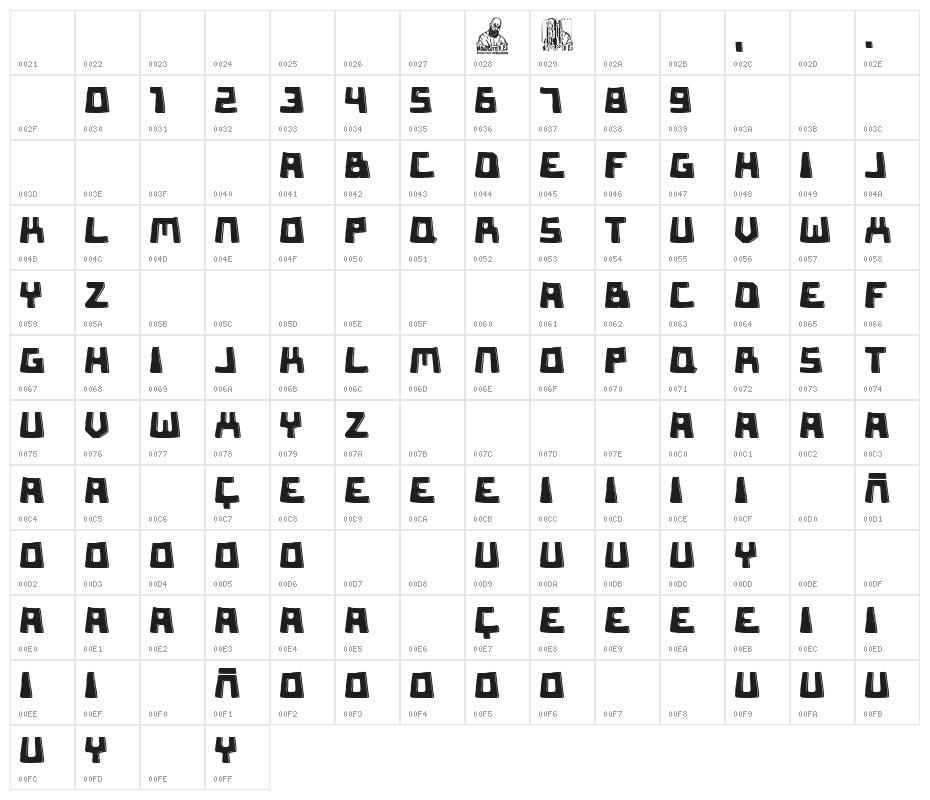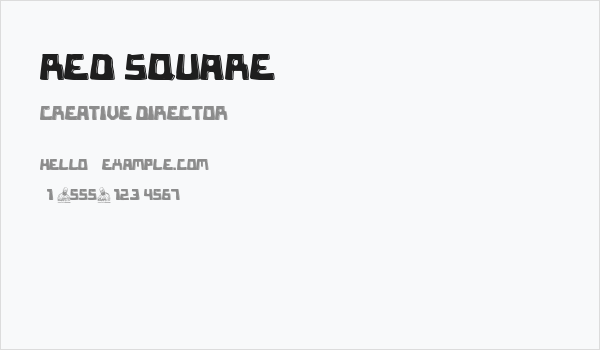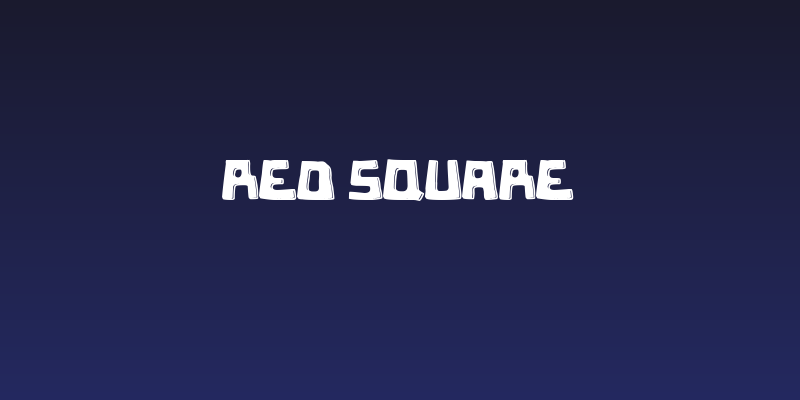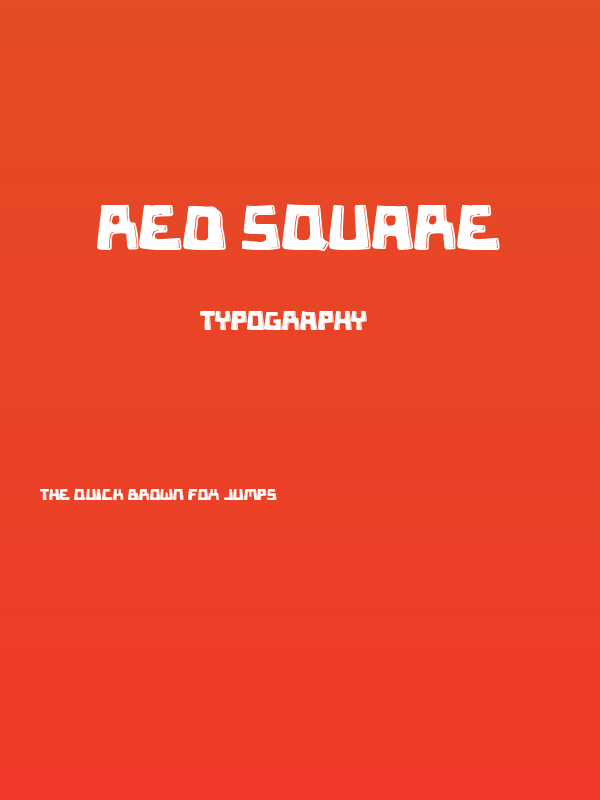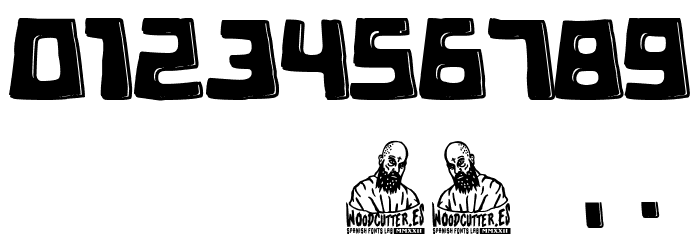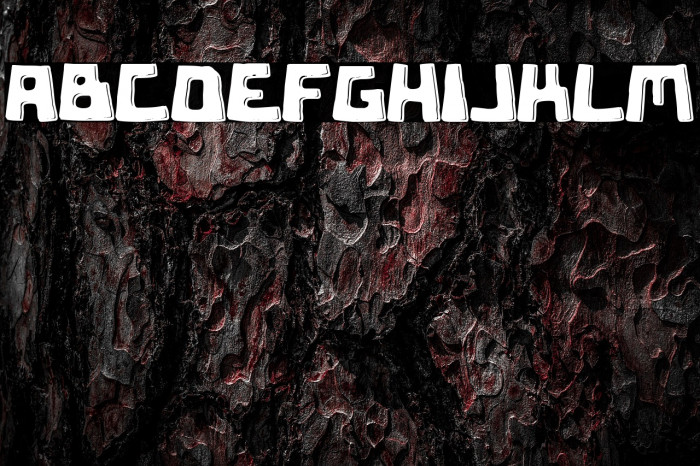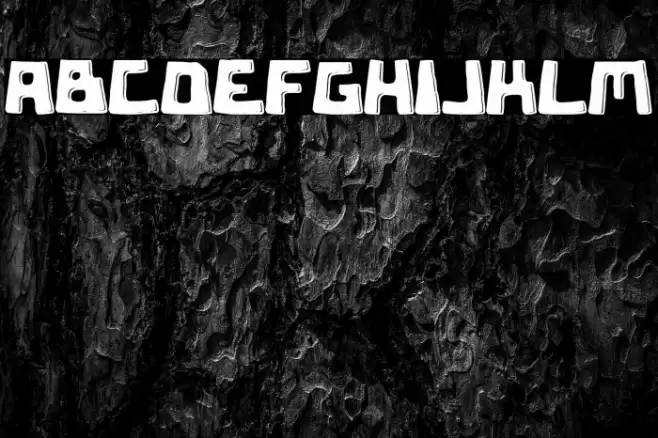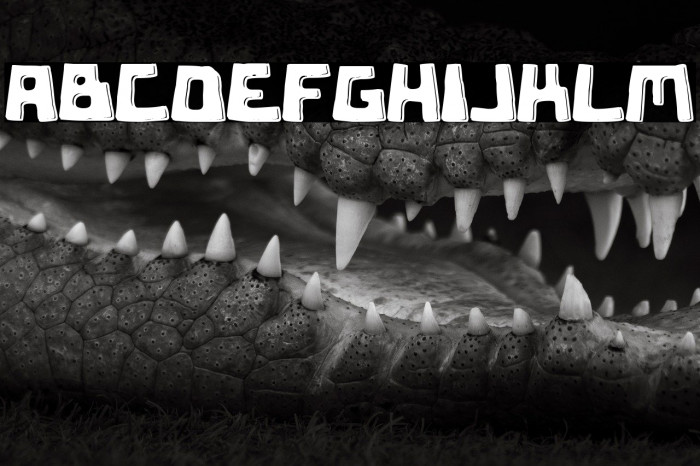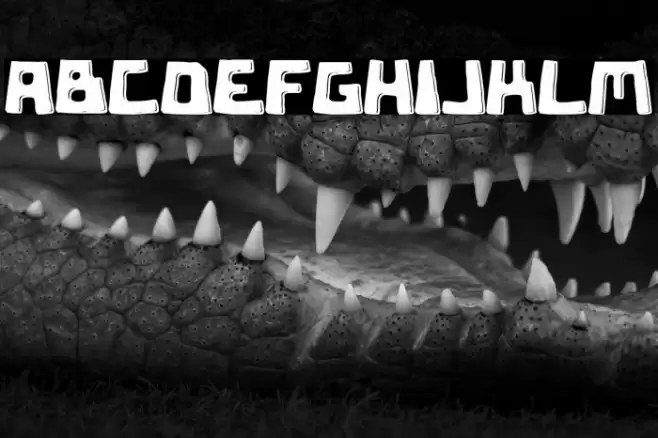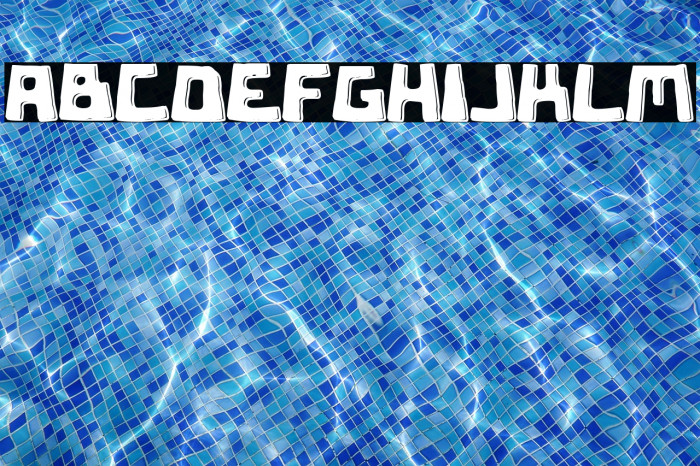
Red Square Font
| Style général | Playful and Quirky |
| Projets proposés | Ideal for comic books, children's books, posters, and playful branding projects. |